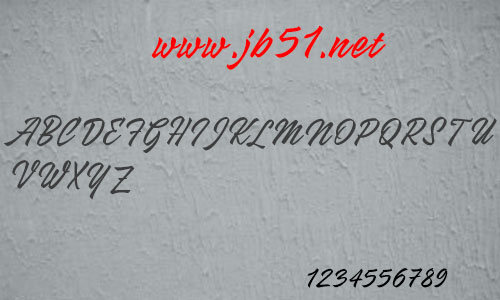
Good Hood英文手寫(xiě)體 ,字體筆觸纖細(xì),書(shū)寫(xiě)流暢灑脫,適合應(yīng)用于藝術(shù)設(shè)計(jì)、平面宣傳設(shè)計(jì)、網(wǎng)頁(yè)設(shè)計(jì),書(shū)法字帖等領(lǐng)域,需要的朋友快來(lái)本站下載使用吧!